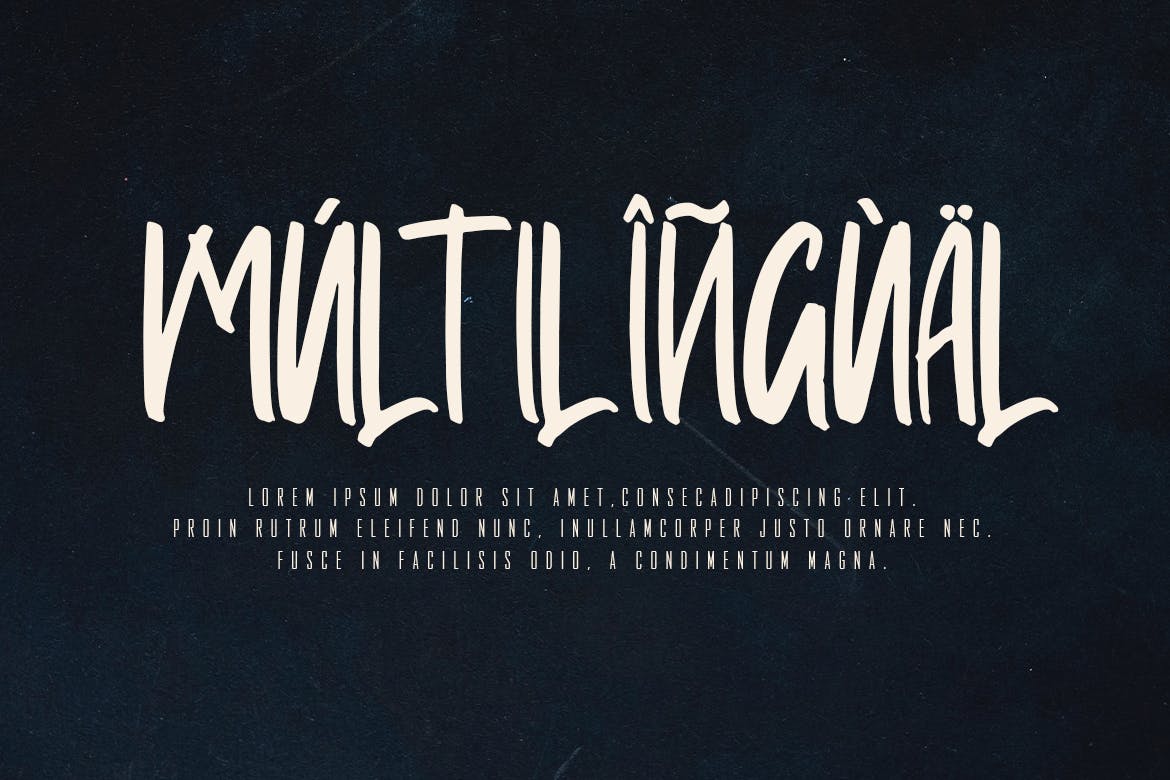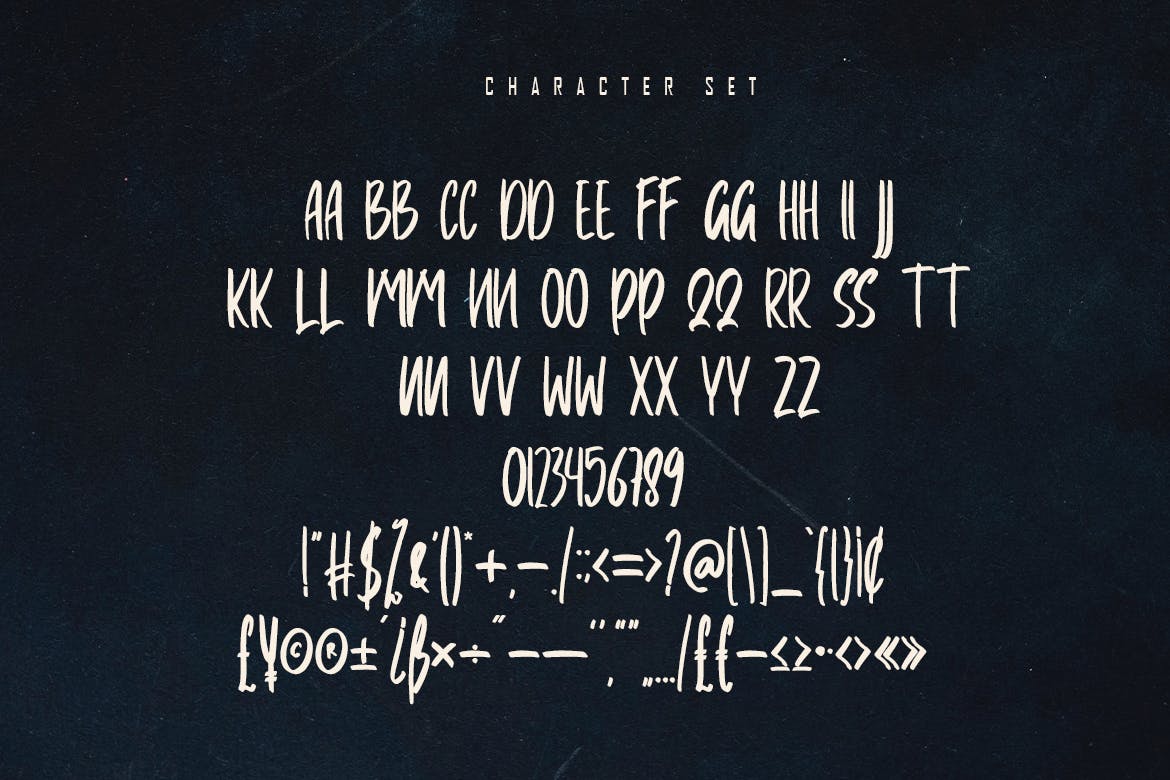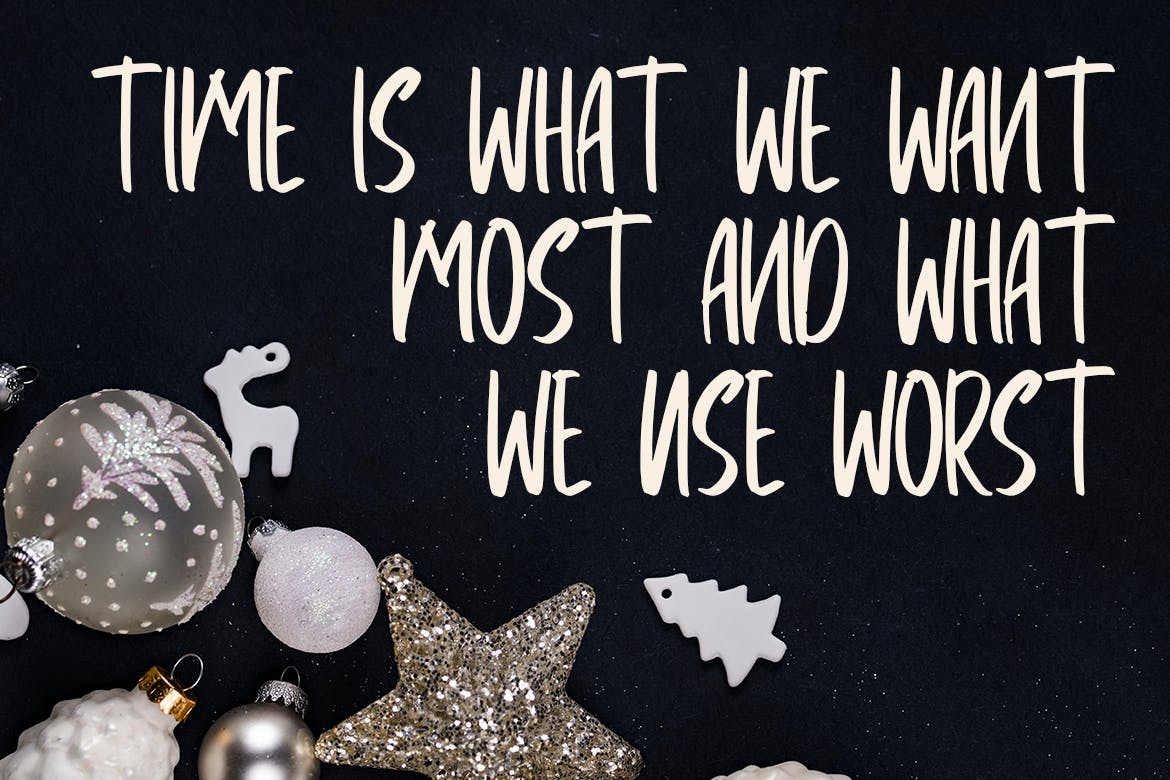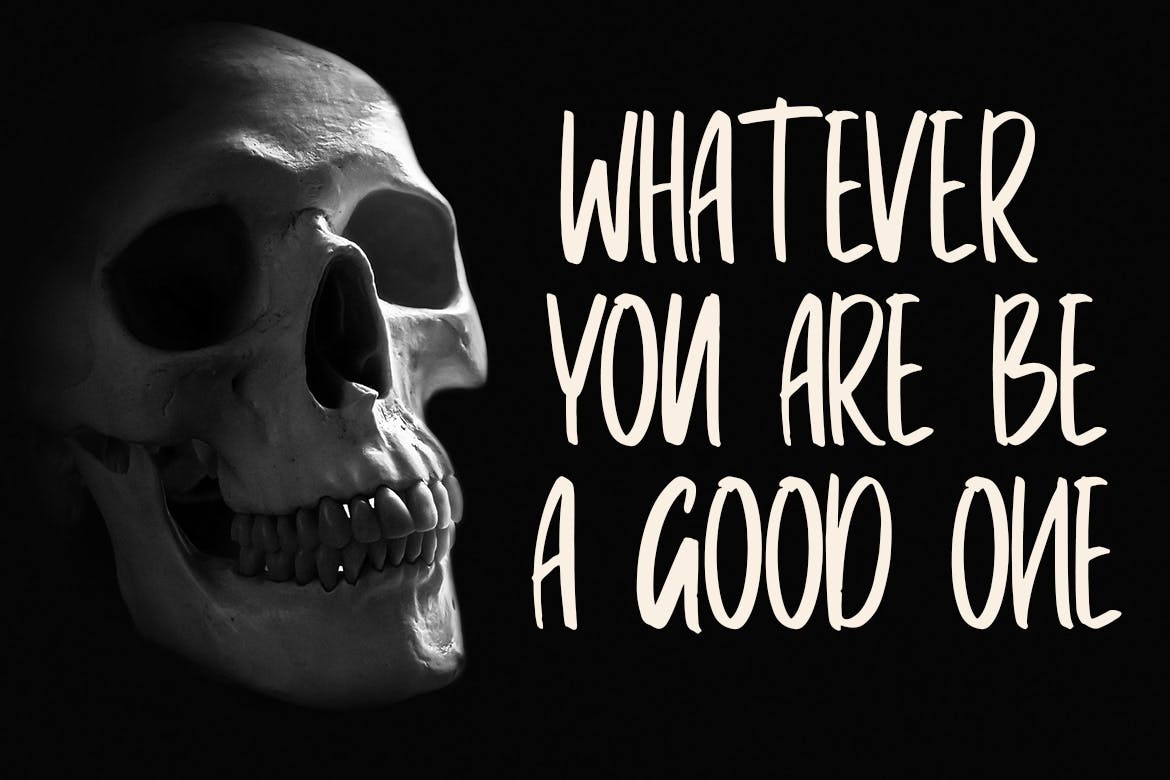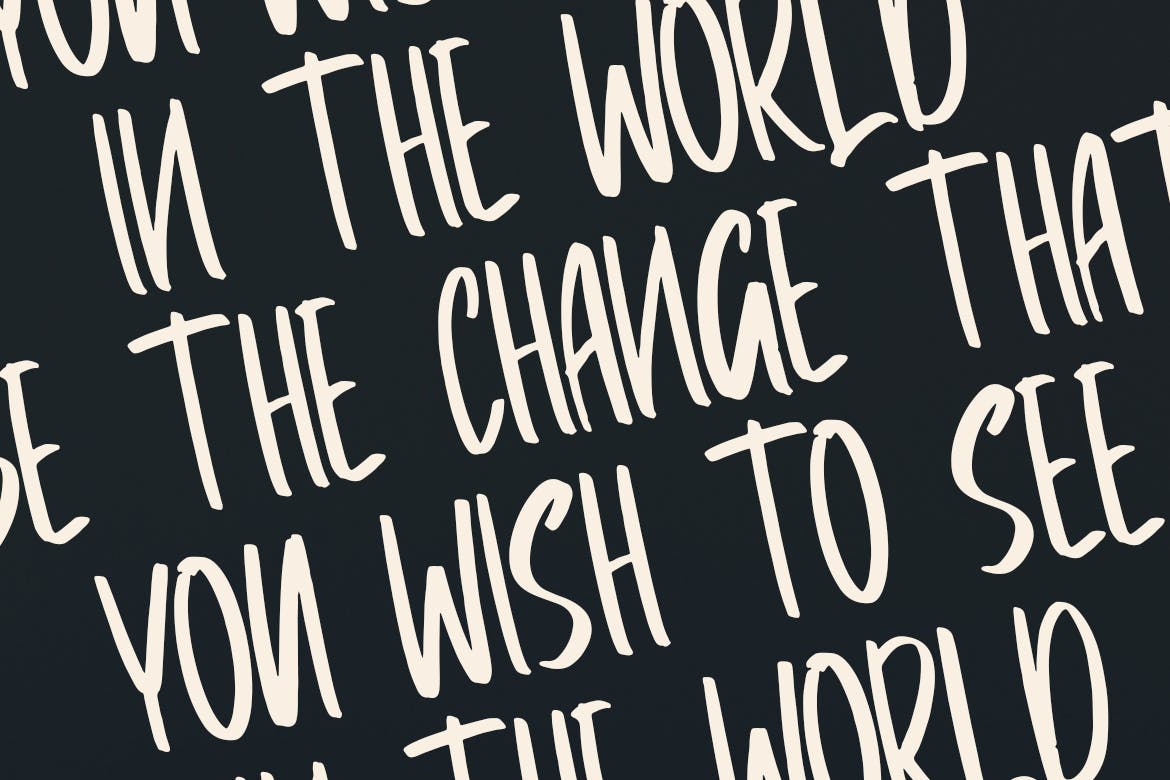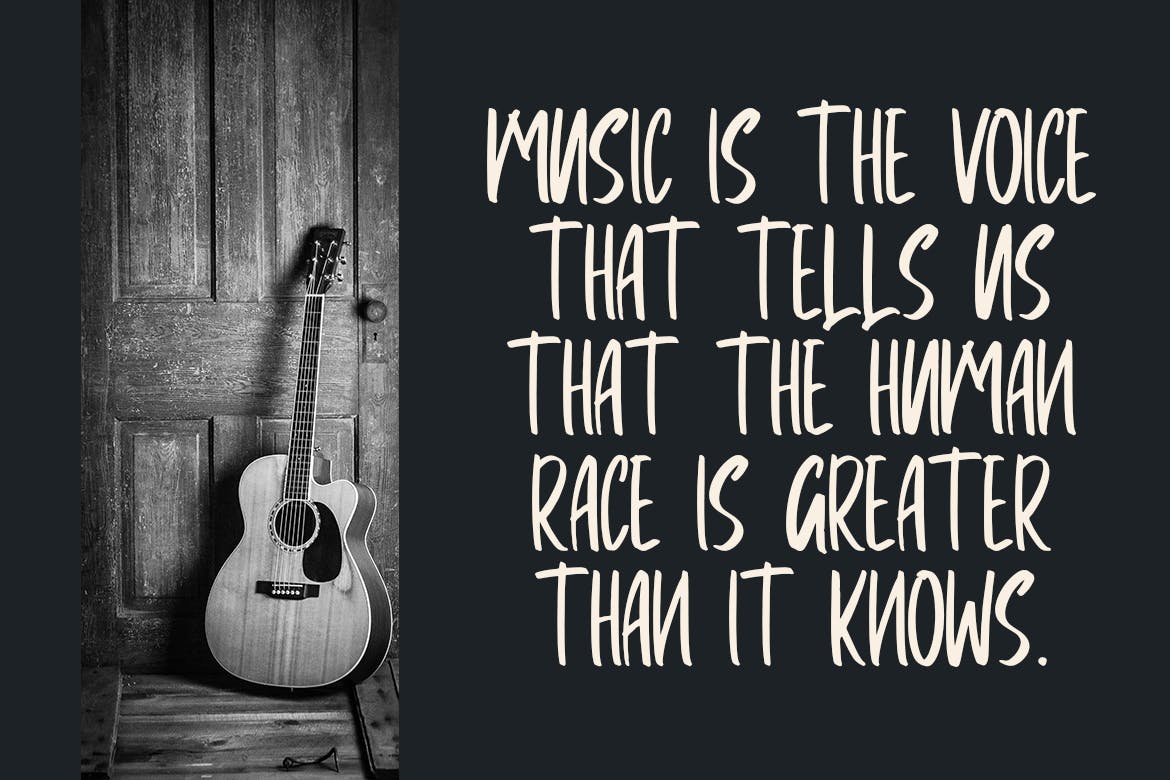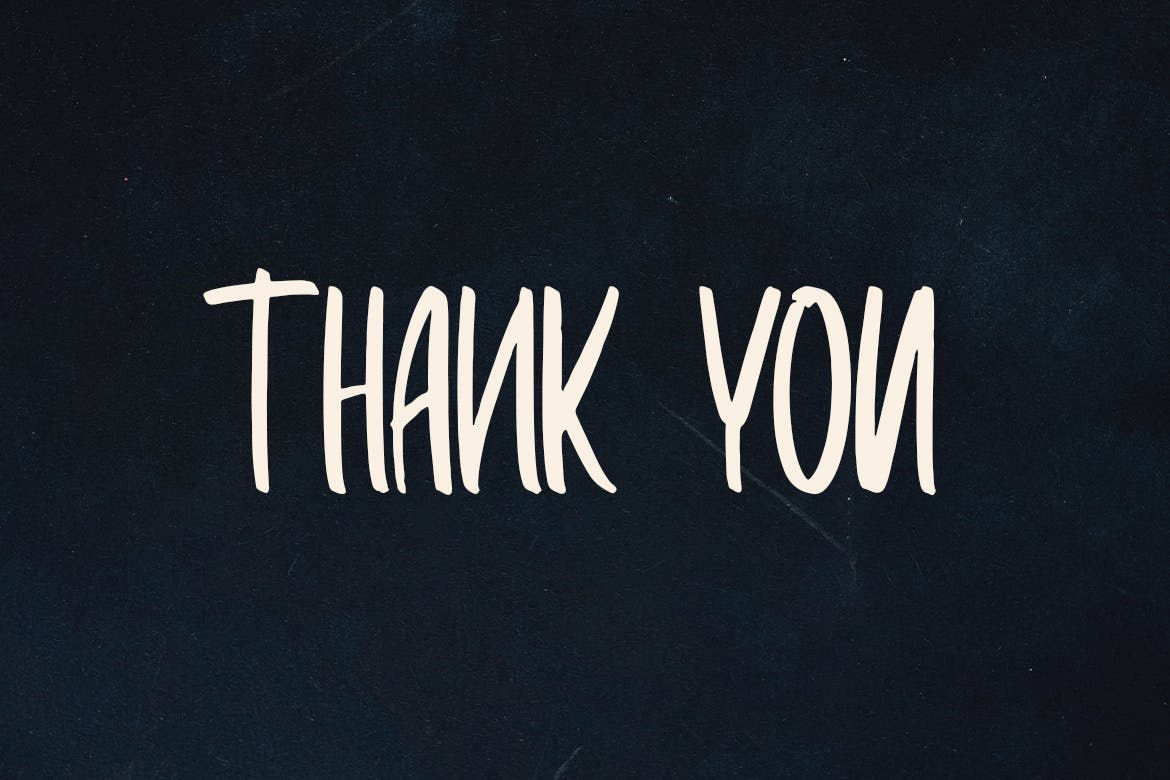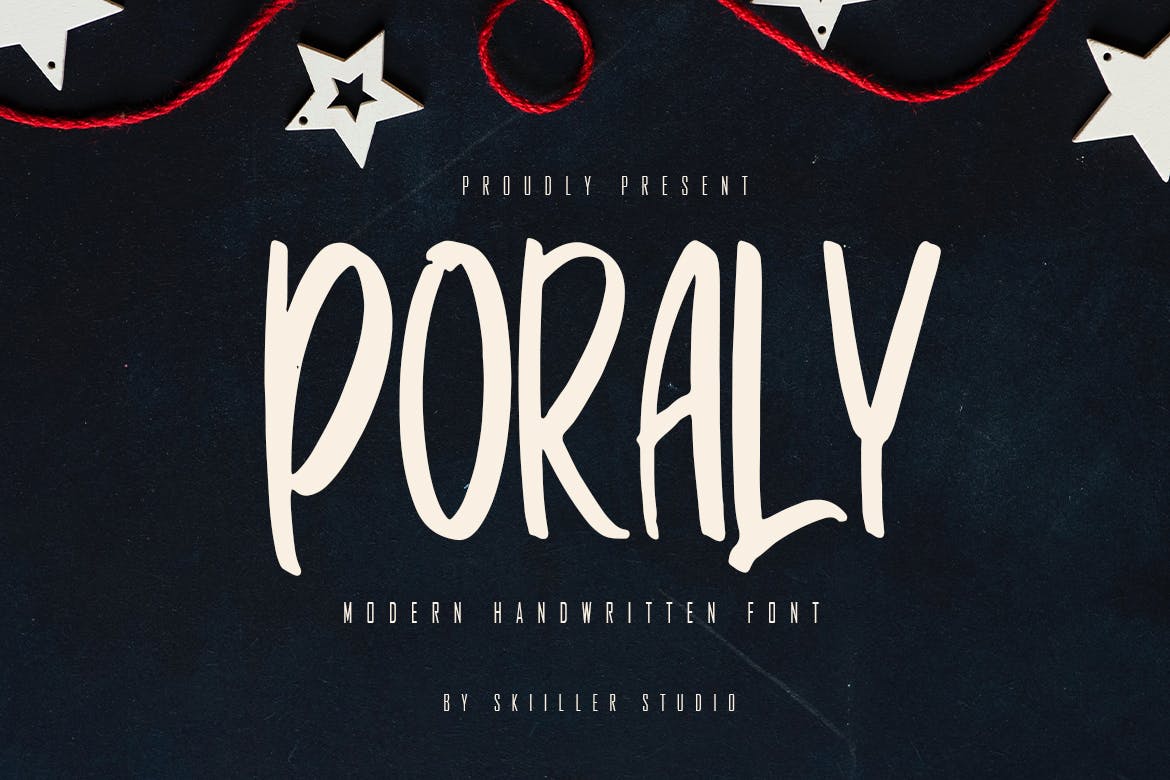
فونت Poraly از حرکات طبیعی و سریع قلممو الهام گرفته شده است. این فونت بهصورت سریع با استفاده از قلممو نوشته شده و بافتی کمی خشک و واقعگرایانه دارد.
لیگاتور
پشتیبانی از زبانهای لاتین پایه (AÀÁÂÃÄÅCÇDÐEÈÉÊËIÌÍÎÏÑOØÒÓÔÕÖUÙÜÚÛWYÝŸÆß)